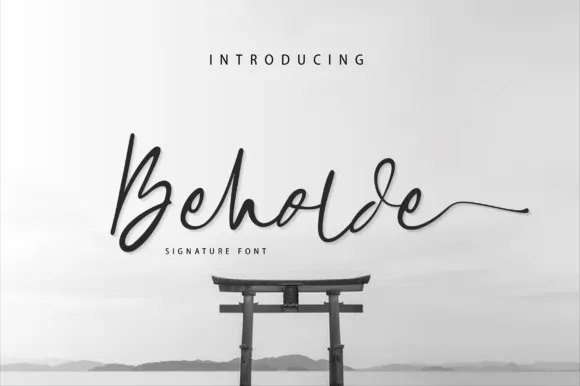
Beholde Font – Fonte Grátis
Beholde Font
Esta é uma fonte script que foi criada pelo fanastudio, apresentando um estilo elegante e delicado. Com uma vibe limpa, fina e suave, ela se destaca como a escolha ideal para qualquer projeto de design que deseje incorporar. A fonte Beholde Signature oferece um toque tipográfico incrível, perfeito para diversos projetos, incluindo logotipos e marcações, convites, estaçãoários, designs de casamentos, posts nas redes sociais, anúncios, embalagens de produtos, design de produtos, etiquetas, fotografias, marcas d’água, eventos especiais ou qualquer projeto que precise do toque autêntico da escrita a mão. Ideal para quem busca uma fonte elegante e delicada para seus designs, sem dúvida será um grande acréscimo à sua coleção de recursos gráficos.